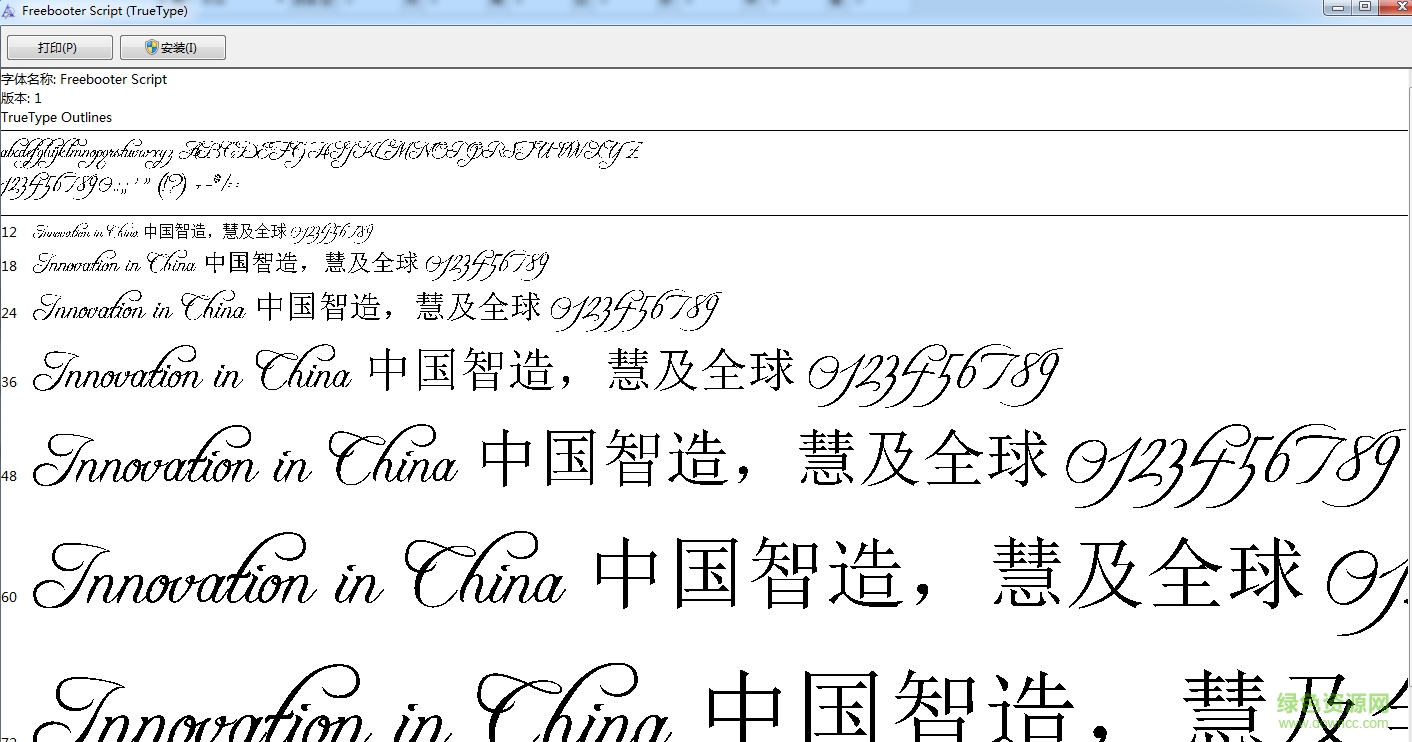
freebooter script字體是一款極具個(gè)性的花體字體,字形優(yōu)美漂亮,活潑飛舞,使用這款字體可以使文字看上去更生動,歡迎大家在綠色資源網(wǎng)下載!
Freebooter Script字體是一款自帶花紋的英文字體,字體線條一筆而成,可用于廣告設(shè)計(jì)、網(wǎng)站設(shè)計(jì)、包裝設(shè)計(jì)等各個(gè)領(lǐng)域!